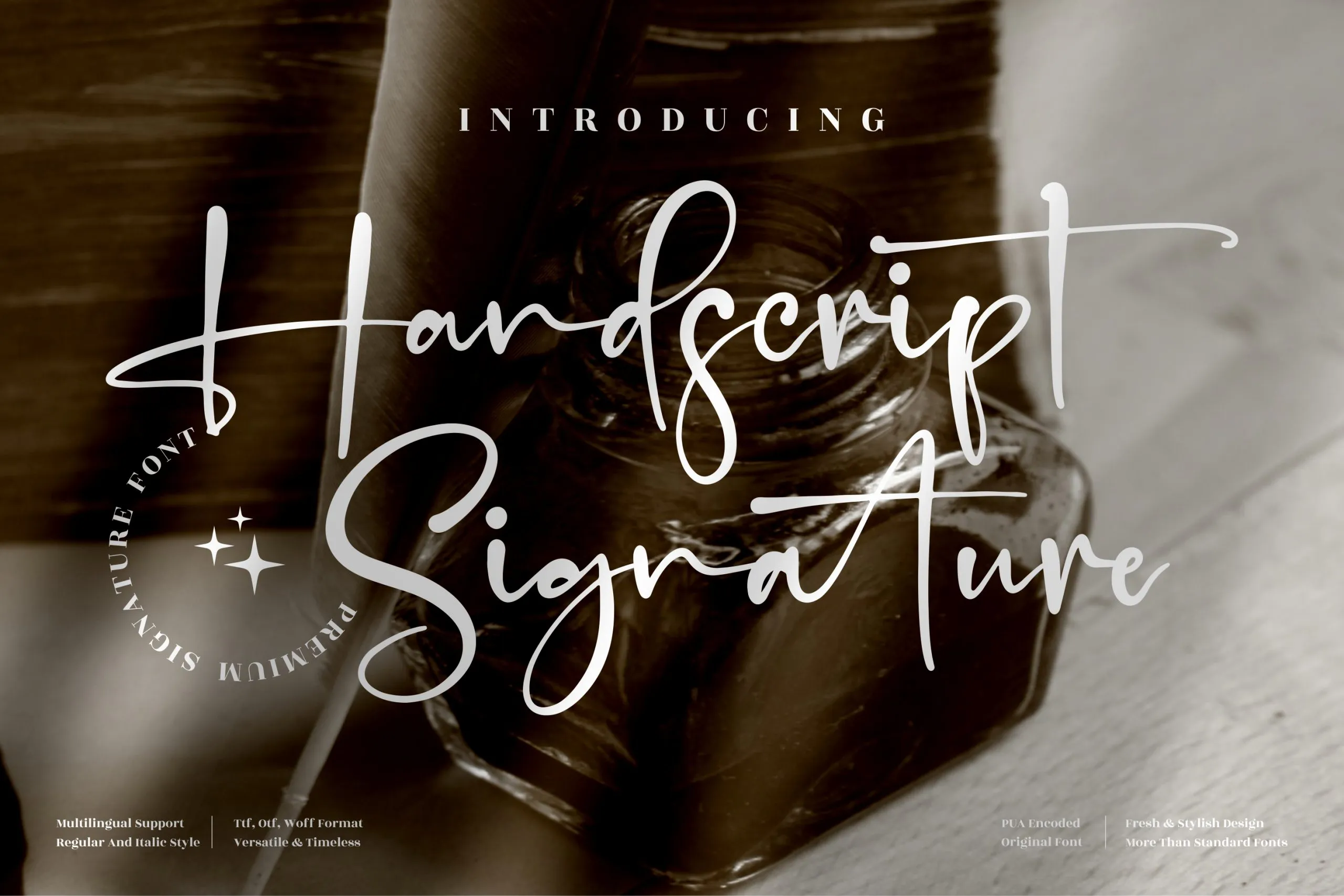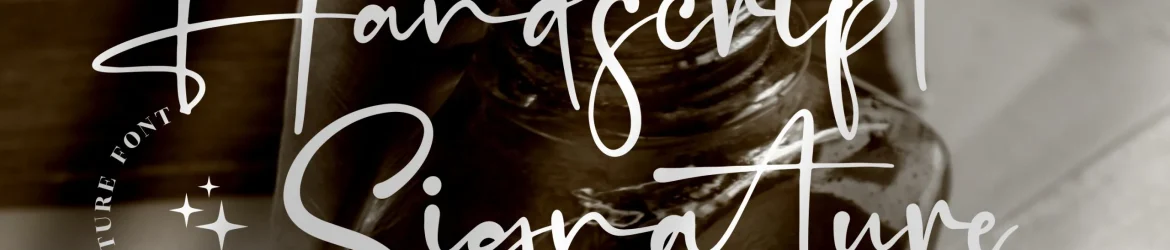
Handscript Signature Font – Download Grátis
Esta é uma fonte de assinatura premium perfeita para projetos variados, desde logotipos e identidades visuais até design de móveis, embalagens de produtos, prateleiras de chá, cartões de post-it, capas de livros, cards de visita, convites, cartões festivos, rótulos, fotografia, marca d’água e eventos especiais. Seja para o seu projeto mais luxuoso ou sofisticado, esta fonte oferece um toque inconfundível de elegância que fará sua produção se destacar. A fonte Handwritten Signature Font foi criada pelo designer perspectype e está disponível como uma opção versátil em nossa gama de fonts. Seja para ilustrar seus projetos gráficos ou dar um toque especial a qualquer projeto, esta font oferece nuances únicas que irão distinguir seu design do resto da multidão. Não importa o tipo de trabalho que você está desenvolvendo – seja ele digital ou físico, essa fonte será uma ótima escolha para manter sua identidade visual única e inovadora.